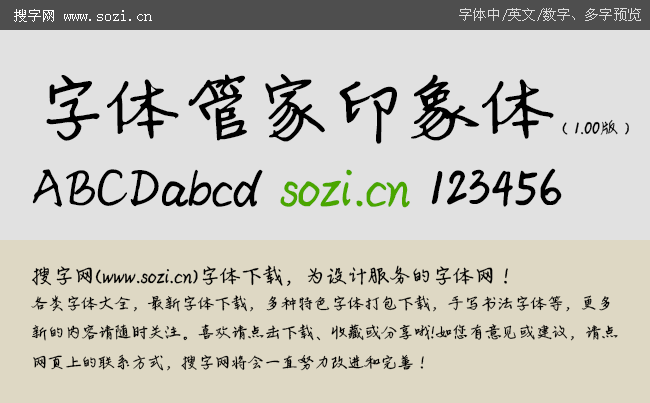
字體管家印象體
搜字網(wǎng)提供一款字體管家印象體中文書法字體下載,字體管家印象體是一款手寫風(fēng)格的鋼筆書法字體,字體書寫流暢,字形大方,整體效果十分出色,適合應(yīng)用于廣告設(shè)計(jì)、名片設(shè)計(jì)、包裝印刷、產(chǎn)品設(shè)計(jì)等應(yīng)用。